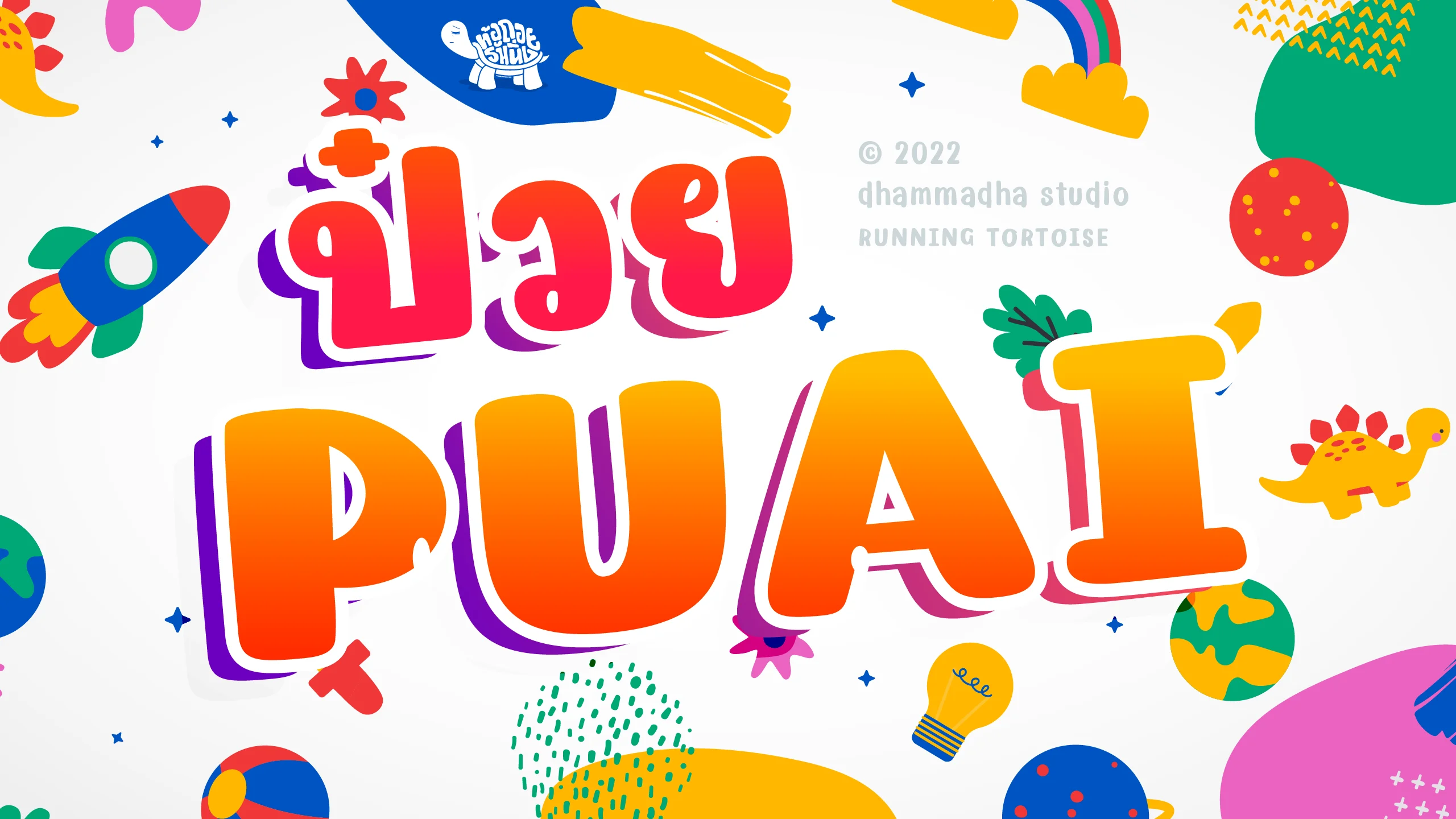
ชุดอักษรลายมือที่ถ่ายทอดความเป็นธรรมชาติและเป็นกันเองอย่างถึงที่สุด โดยเป็นผลงานการออกแบบจากแอดมินเพจ ท้อถอยรันนิ่ง / RUNNING TORTOISE ผู้อยู่เบื้องหลังไอเดียสุดสร้างสรรค์อย่างฟอนต์ "ดองเต่า | DONGTAO" ที่หลายคนคุ้นตา โดยในครั้งนี้ "ป๋วย" มาพร้อมกับบุคลิกที่ดูเรียบง่าย สบายตา และเข้าถึงง่ายยิ่งขึ้น มอบความรู้สึกเหมือนการเขียนด้วยลายมือจริงๆ ที่แฝงไว้ด้วยความจริงใจและมีชีวิตชีวาในทุกเส้นสาย ความพิเศษของฟอนต์ชุดนี้อยู่ที่ความใส่ใจในรายละเอียดเพื่อให้การใช้งานดูเป็นธรรมชาติที่สุด เราจึงจัดเต็มด้วยชุดอักษรทางเลือก (Alternative Glyphs) มากมายที่ช่วยลดความซ้ำซ้อนของรูปตัวอักษร ทำให้การจัดวางข้อความดูมีจังหวะที่ลื่นไหลเหมือนลายมือเขียนสดจริงๆ เหมาะอย่างยิ่งสำหรับงานออกแบบที่ต้องการความเป็นส่วนตัว ไม่ว่าจะเป็นบันทึกการเดินทาง การจัดวางคำโปรยในสื่อโซเชียล หรือการสร้างสรรค์งานกราฟิกสไตล์ไลฟ์สไตล์ที่ต้องการความอบอุ่นและเป็นเอกลักษณ์เฉพาะตัว